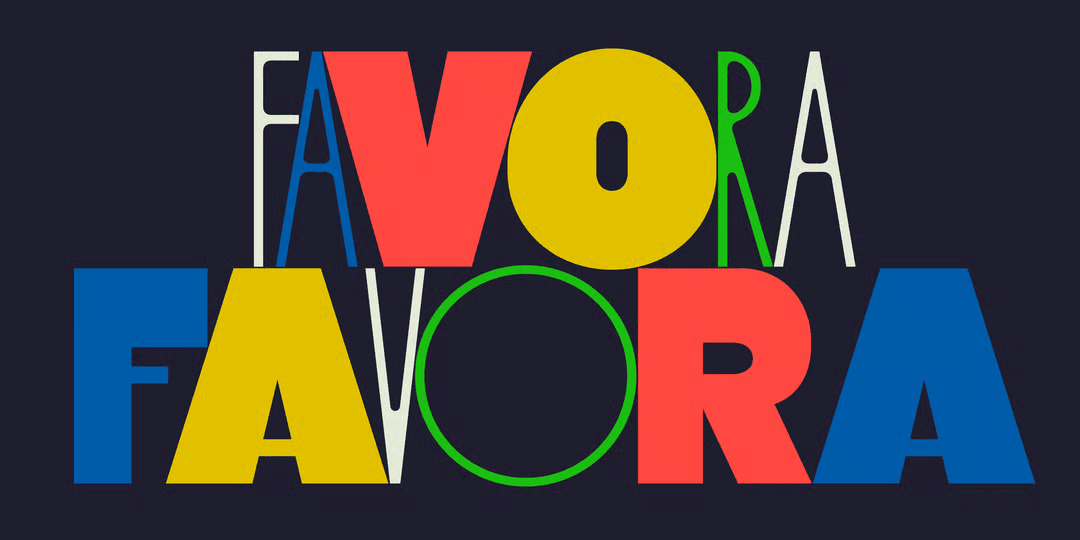
Favora
超極太と超極細のコントラストが凄まじいディスプレイサンセリフ。1ファイルしかない書体だが、大文字グリフに超極太、小文字グリフに超極細の大文字が割り当てられた変わった書体で、細い方は丸い C, G, O, Q 以外はプロポーションまで極細となっている。ランダムに組めば見ての通り楽しい演出が可能ではあるが、なかなかセンスよく使うにはハードルが高いと思う(笑)。まぁ $10 程度の安い書体なので気軽に試してみてほしい。